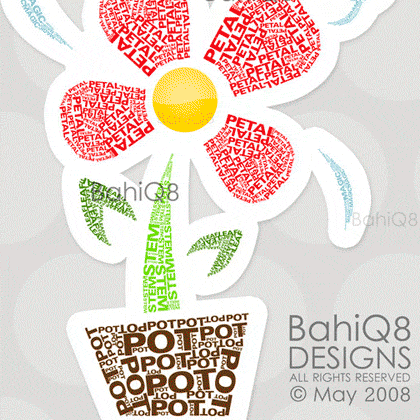
Source d’inspiration | i Love Typography
I LOVE TYPOGRAPHY
Allez piqûre de rappel: i Love Typography toujours indispensable pour aller y pêcher des idées, des ressourcements, et pourtant bien souvent je reste sur ma faim. Pourquoi. Sans doute pour une raison très simple, les images publiés sont fréquemment déconnectés de l’histoire qui les a généré. Du coup il manque une dimension sémantique et nous reste juste les effets de style. Et là gros problème. Plus de la moitié des travaux exposés sur le blog peuvent être «sourcés» auprès des grands maîtres de la typographie et de l’art graphique des années 80-90. Voire plus ancien. Le <M> par exemple me fait penser aux travaux de Lubalin et Dorsman , la composition en rouge et noir aux transgressions de David Carson , etc. Pour dire juste que le contexte, qui légitime ces créations fait souvent défaut sur tous les blogs «vitrines-résonnateurs». On se contente de montrer (c’est déjà pas mal), mais point d’analyse, de décryptage.
Bien sûr une autre réflexion: tous les jeunes du monde entier cherchent à imiter les maîtres, en oubliant bien souvent que la perfection que ceux-ci ont obtenus avec les moyens techniques «old school» datant d’avant les PC/Mac, leur ont demandé des jours et des semaines de création, réalisations méticuleuses où chaque détail était réfléchi, évalué, et pesé. Il n’y avait pas de Cntr Z ou de Pomme Z à l’époque. Tu te trompes, tu recommences. Neville Brody avait déjà évoqué en 2003 ou 2002 je crois cette perte d’appropriation de la création graphique… il faut lire son discours de New-York que j’ai intitulé le Blues de Neville Brody… et il faut aussi le lire entre les lignes en allant visiter les billets que j’ai écrit sur son œuvre magistrale publié à la fin des années 80 et début 90.